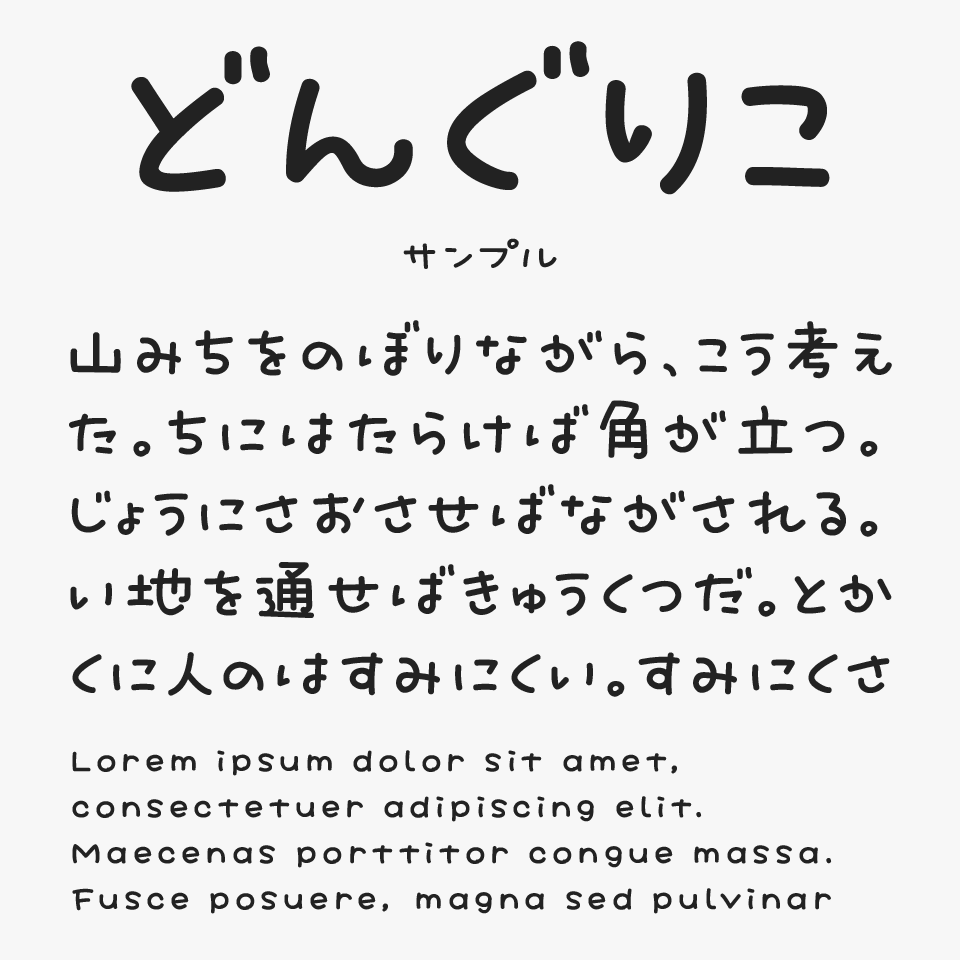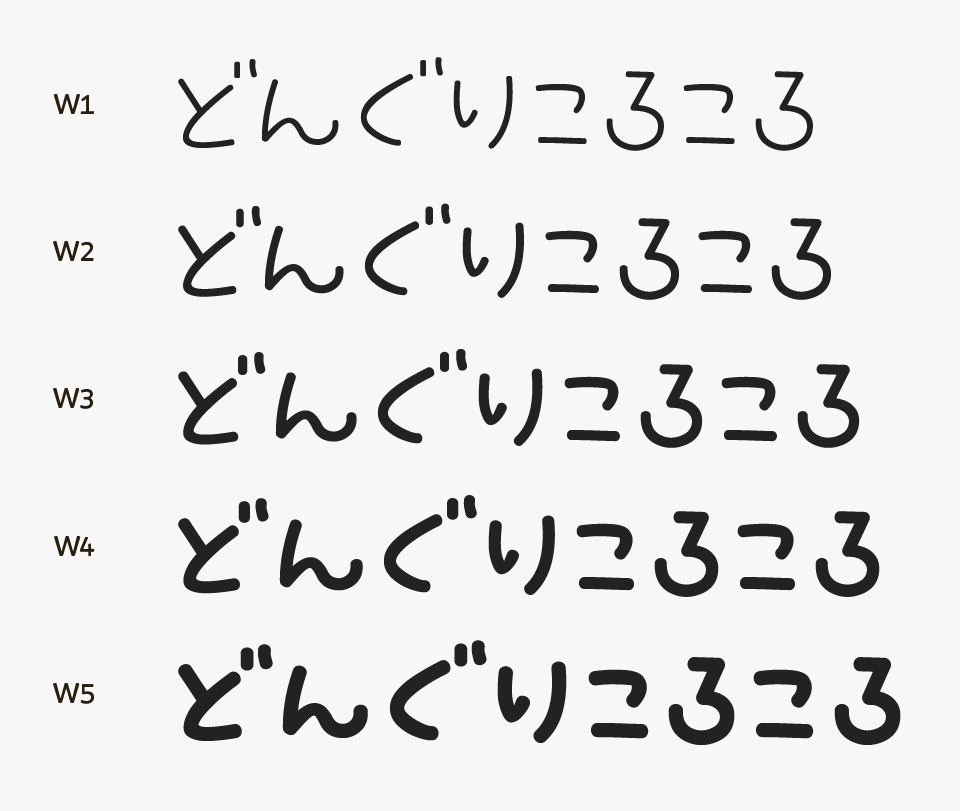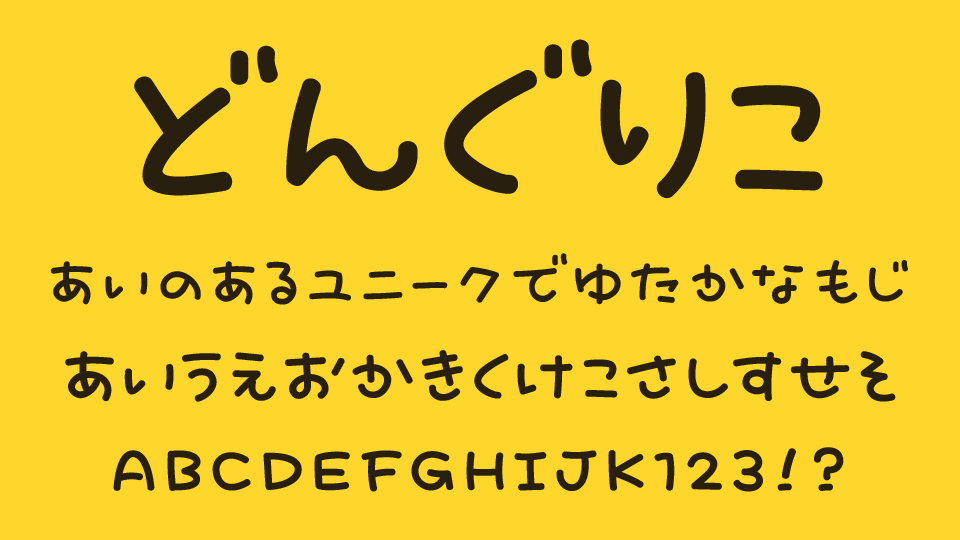
どんぐりこフォントは、丸みのある素朴な文字に、自然な揺らぎを取り入れた親しみやすい手書きフォントです。
線の太さや文字のバランスにほどよいムラがあり、子どもが丁寧に書いたような無邪気さと温かみを感じられる温かい手書きフォントです。飾りすぎないシンプルな表情なので、可愛らしさと読みやすさを両立した使いやすいフォントです。
絵本や保育・教育関係、ハンドメイド作品、カフェ、SNS投稿など、やさしく親近感のあるデザインにぴったりなフォントです。
通常版(有料版)のみとなっていますが、太さを変えられるバリアブルフォントとなっています。太さが変わるとまた違った雰囲気となる面白いフォントです。
どんぐりこフォントを、ほかの素朴でかわいらしい手書きフォントと比較してみると、子どもの手書きのような無邪気さと、自然な丸みが特徴のフォントとなっています。
比較フォントは、「梅干ナチュラル」「ころたん」「風花」「ちひろもじ」「ゆな字」と使用していますが、どれも温かみのある手書きフォントなので、ぜひあわせてチェックしてみてください。